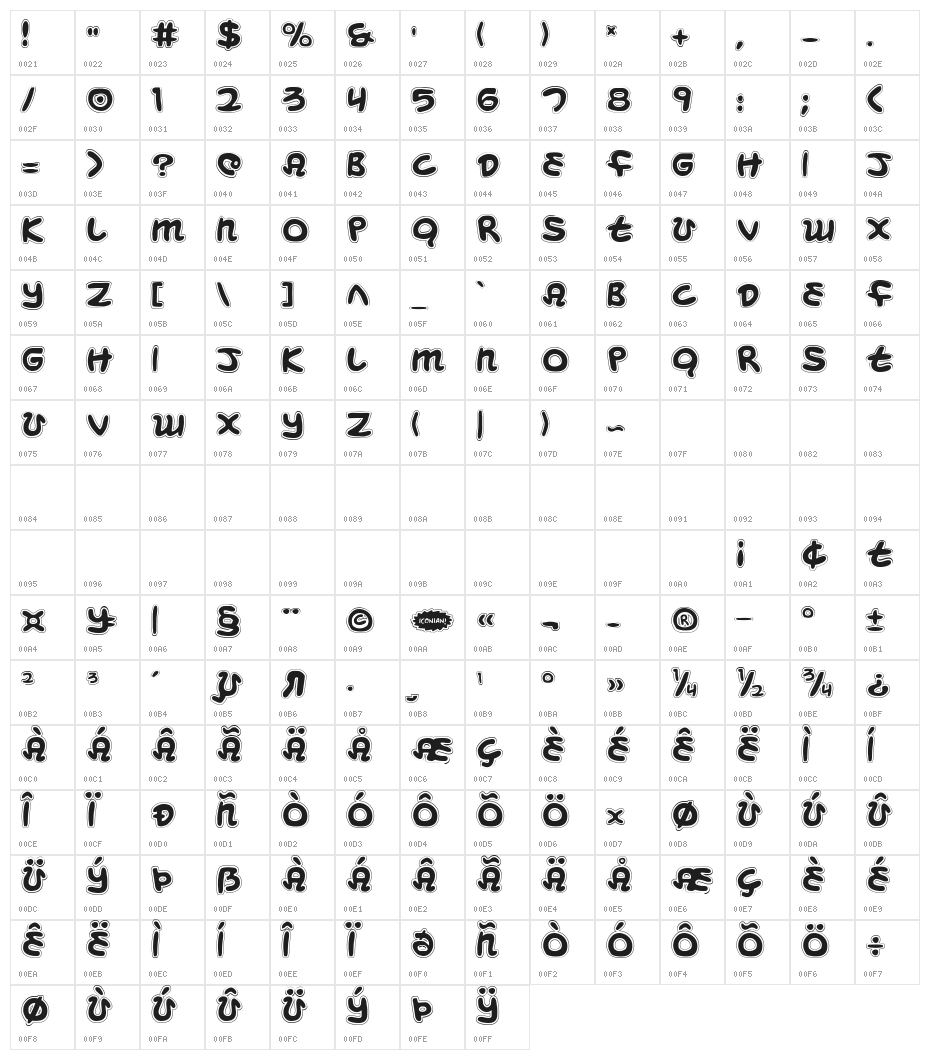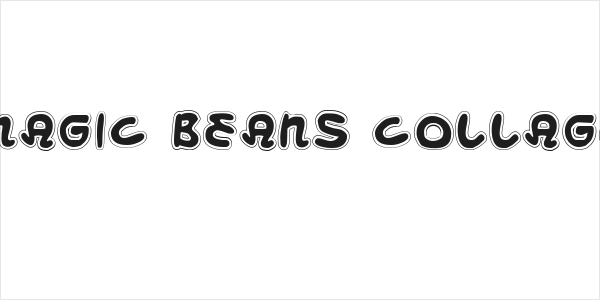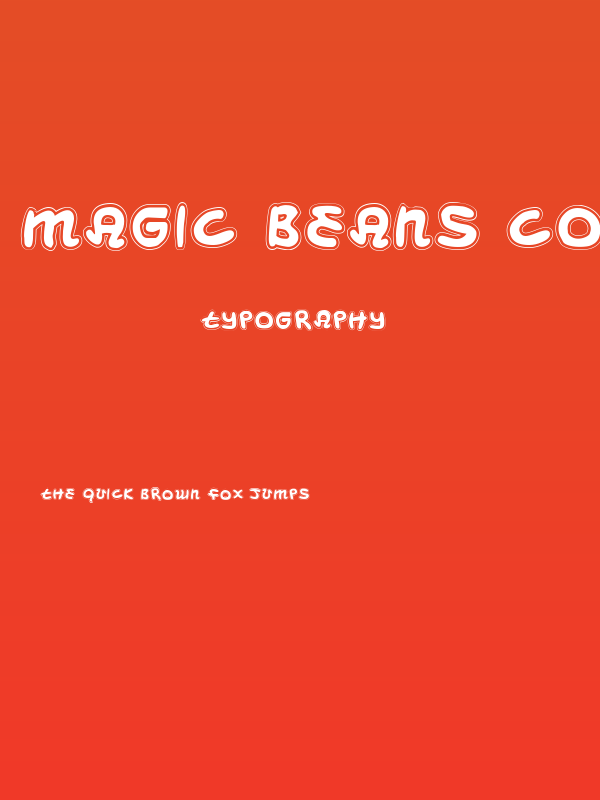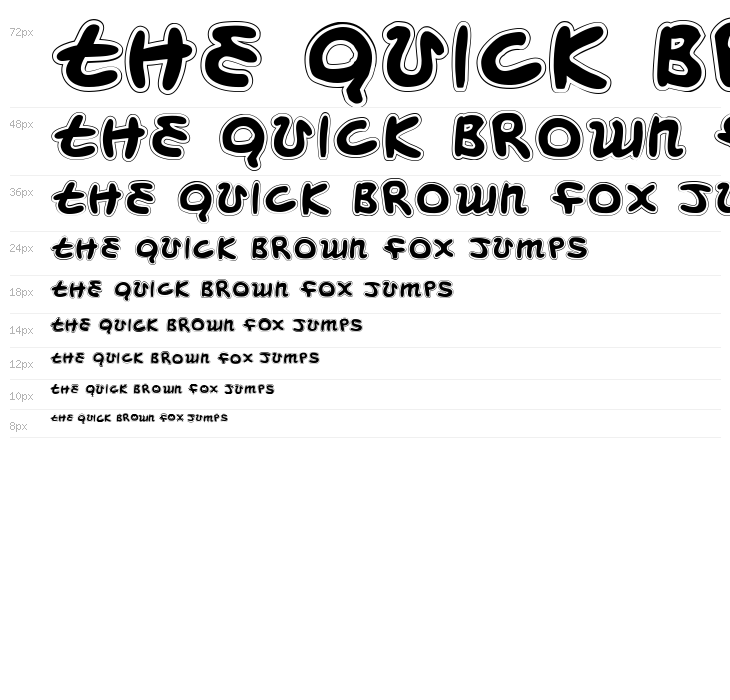
Magic Beans Collage Font
| समग्र शैली | Playful, Cartoonish |
| उपयोग का मामला | Headlines, Logos, Posters |
| सुझाए गए प्रोजेक्ट | Ideal for children's books, playful branding, party invitations, and creative posters. |